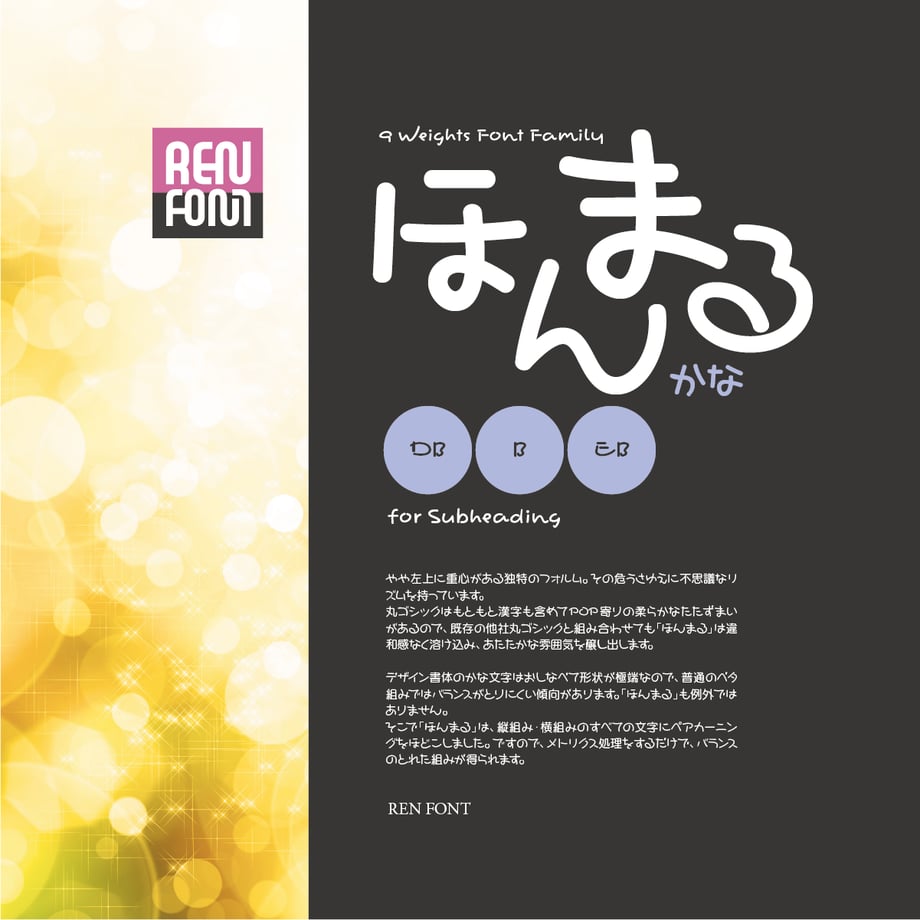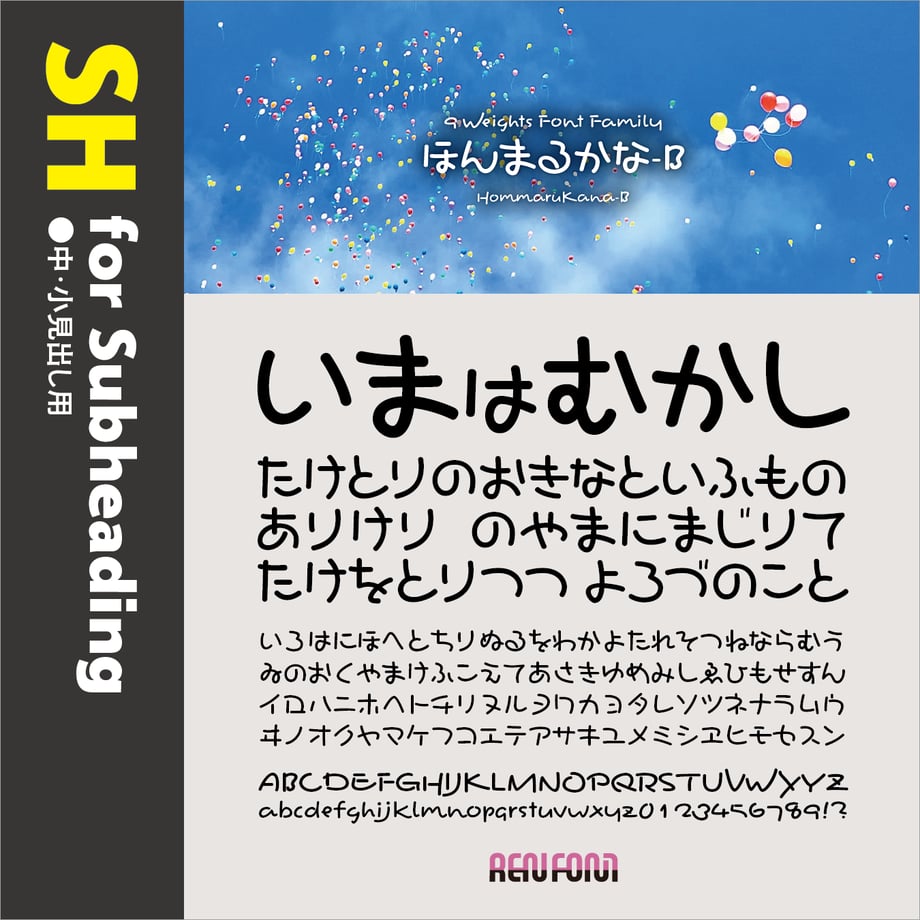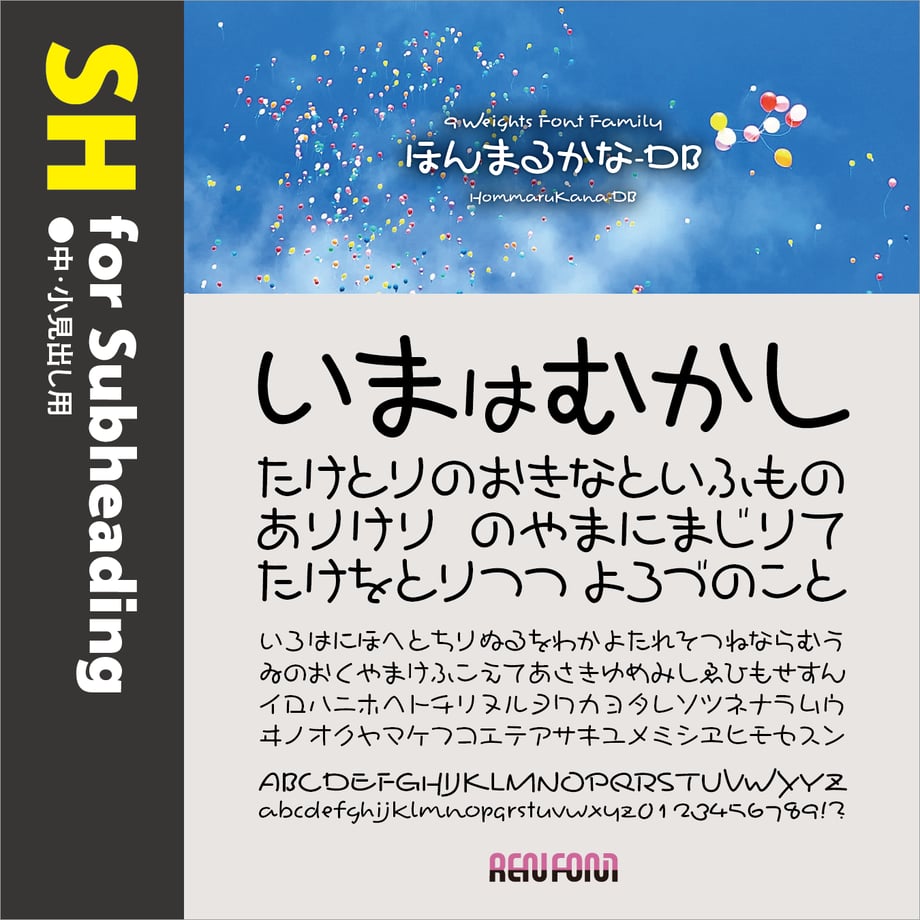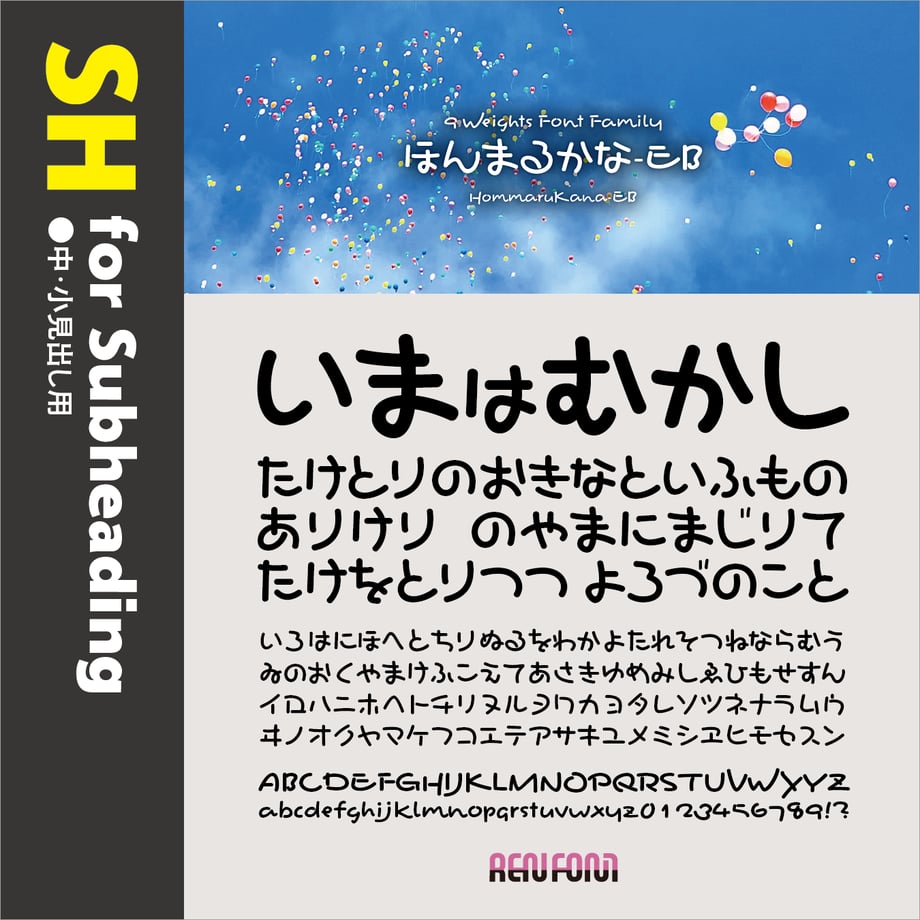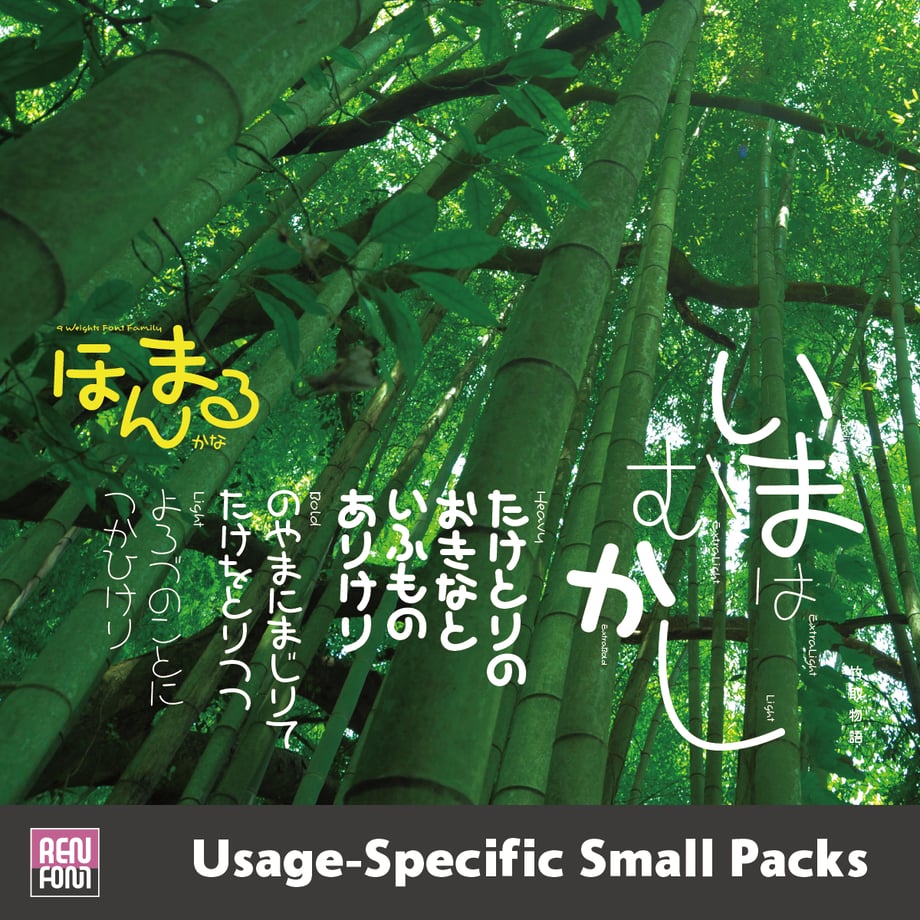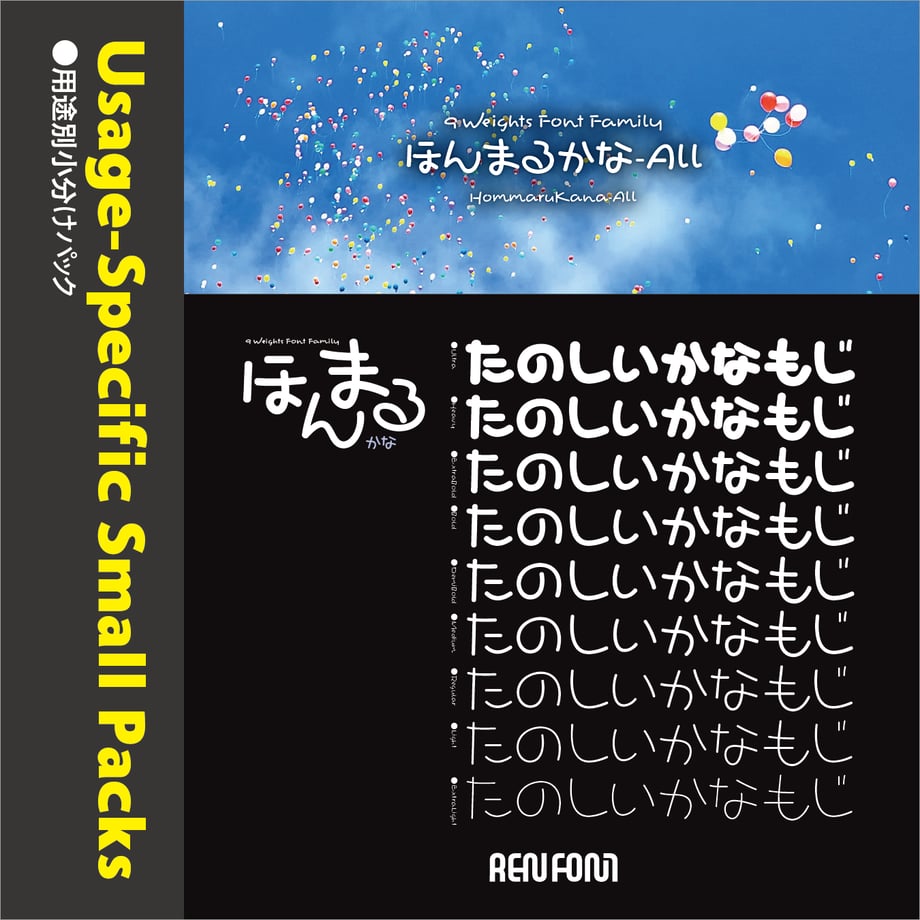
ほんまるかな-SH(中・小見出し用)DB/B/EB
おとなの味な丸もじ
ほんまるかな 9ウェイトファミリー / OpenType
かすかに筆文字の名残り、味わいのある丸もじ。
やや左上に重心がある独特のフォルム。その危うさゆえに不思議なリズムを持っています。
丸ゴシックはもともとPOP寄りの柔らかなたたずまいをしており、デザイン書体との相性がよい書体。「ほんまる」は既存の他社丸ゴシックと組み合わせても違和感なく溶け込み、あたたかな雰囲気を醸し出します。
デザイン書体のかな文字はおしなべて形状が極端なので、普通のベタ組みではバランスがとりにくい傾向があります。「ほんまる」も例外ではありません。
そこで「ほんまる」は、縦組み・横組みのすべての文字にペアカーニングをほどこしました。ですので、メトリクス処理をするだけで、バランスのとれた組みが得られます。
一般的な丸文字とは異なり、かすかに筆文字の名残りを感じる、味わいのあるフォルムに仕上げました。キャッチフレーズ「おとなの味な丸もじ」はそこからきています。
漢字で書くと「奔丸」。既存の行書書体「奔行」の流れを汲んでいます。
重心を左上に置いているため不安定で、リズミカルに踊っているような動きのある楽しい印象を与えます。
丸ゴシックの宿命として硬い内容の文章には不向きですが、「ほんまる」は動的要素が強いので、カジュアルなものに訴求力を発揮します。
従属欧文は当社の場合、比較的オーソドックスなものにしていますが、「ほんまるかな」はスクリプト体です。
跳ねる文字もあれば跳ねずに止まる文字もあり、破天荒でバラエティに富んだ、リズムあふれる書体になっています。使っているだけでウキウキしてくる、無条件で楽しい書体です。